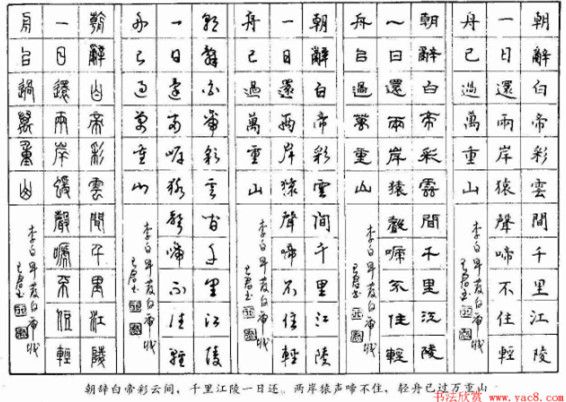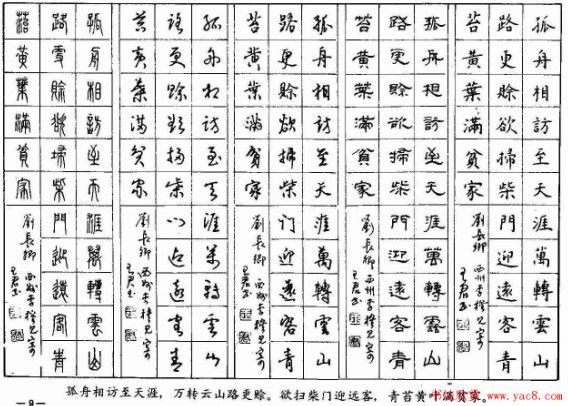
五体钢笔字帖《历代绝句百首》练字帖下载(共100张)
本钢笔练字字帖模板共有100张练字字帖组成,每张字帖上面为一首古诗绝句,分为楷书字体、隶书字体、行书字体、草书字体、篆书字体共5种字体来书写,故名为五体钢笔练字字帖,适合成人练字时使用,修身养性、调节情操使用。
绝句古诗列举如下几个(具体看字帖模板):
桃花溪
作者:张旭
隐隐飞桥隔野烟,石矶西畔问渔船。
桃花尽日随流水,洞在清溪何处边。
咏柳
作者:贺知章
碧玉妆成一树高,万条垂下绿丝绦。
不知细叶谁裁出,二月春风似剪刀。
三日寻李九庄
作者:常建
雨歇杨林东渡头,永和三日荡轻舟。
故人家在桃花岸,直到门前溪水流。
春行寄兴
作者:李华
宜阳城下草萋萋,涧水东流复向西。
芳树无人花自落,春山一路鸟空啼。
酬李穆见寄
作者:刘长卿
孤舟相访至天涯,万转云山路更赊。
欲扫柴门迎远客,青苔黄叶满贫家。